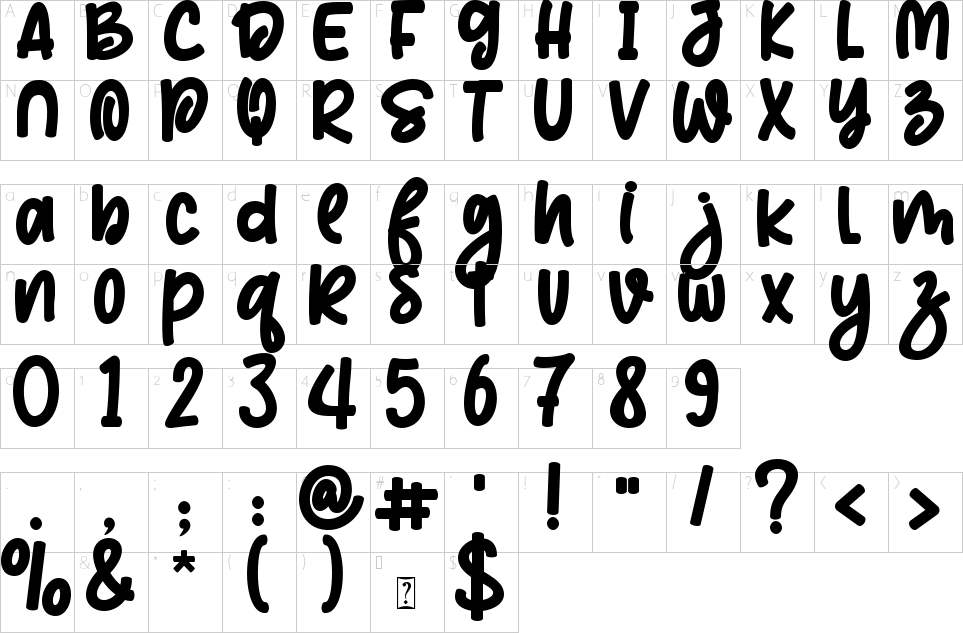
Descubra Mikhaloo, uma fonte grátis disponível para Windows e Mac. Desenvolvida por Thomas Aradea, essa fonte já foi baixada mais de 2 mil vezes, reforçando sua qualidade e versatilidade para uso em designs variados. Ideal para quem busca opções sem custos, Mikhaloo oferece uma fonte limpa e elegante que se destaca em design gráfico e editorial. Descubra por si mesmo o charme desta fonte e experimente incorporá-la a seus projetos. Comprar e usar Mikhaloo font não tem nenhum custo, tornando-a um excelente recurso para designers e criadores de conteúdo que buscam qualidade sem comprometer o orçamento. Não deixe de baixar e explorar Mikhaloo hoje.